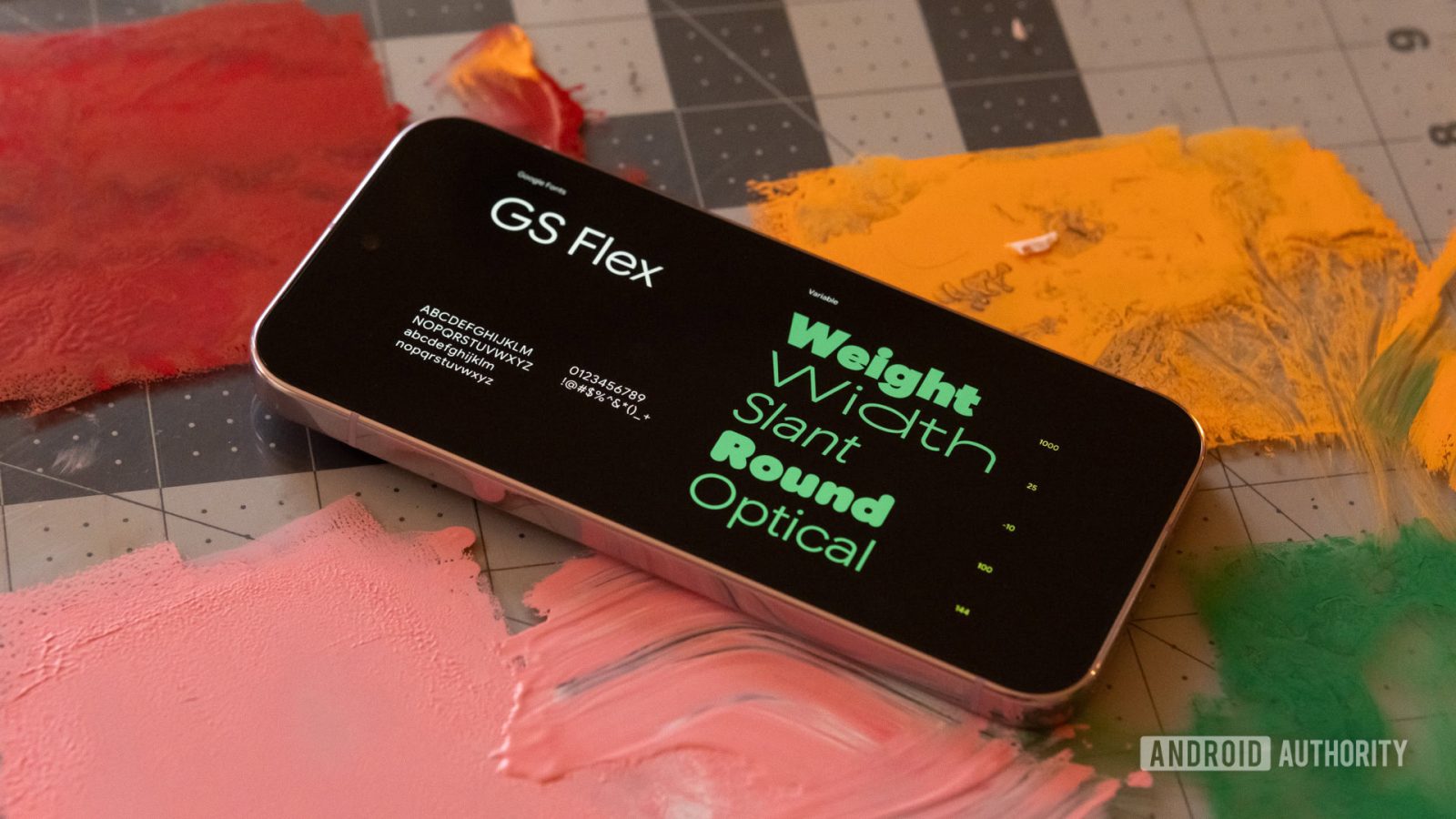
La disponibilità di Google Sans Flex su Google Fonts rappresenta un’importante novità nel panorama delle tipografie open-source. Questo carattere, utilizzato da Google in diversi prodotti, è ora accessibile a tutti gli utenti per un’ampia gamma di applicazioni.
google sans flex: caratteristiche e utilizzo
Google Sans Flex si presenta come un font sans-serif versatile, dotato di cinque assi variabili: peso, grado, inclinazione, larghezza e tonalità. Sebbene il font venga comunemente utilizzato nelle pagine web e nei prodotti Google, la sua capacità di essere modificato consente una personalizzazione che va oltre l’aspetto standard del carattere.
principali vantaggi dell’utilizzo del font
- Versatilità grazie alle sue cinque dimensioni variabili.
- Utilizzabile in contesti sia digitali che cartacei.
- Semplicità nella personalizzazione per adattarsi a diverse esigenze grafiche.
L’introduzione di Google Sans Flex nel repertorio dei caratteri disponibili su Google Fonts segna una significativa evoluzione nell’offerta tipografica per designer e sviluppatori, ampliando le possibilità creative nel design visivo contemporaneo.